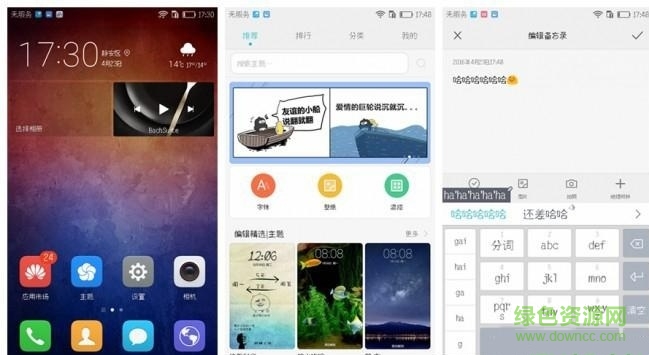
華為p9字體是一款非常漂亮的字體哦,這款字體是華為自帶的字體,當(dāng)時(shí)好像華為商城中是需要付費(fèi)才能下載哦,所以今天小編教大家怎么使用免費(fèi)的華為p9字體??!
注意:此字體偏小一些,在有些界面看上去會(huì)覺得小,可以將手機(jī)系統(tǒng)設(shè)置中的字體調(diào)大就可以了!另外,之前的華為手機(jī),出現(xiàn)過某些應(yīng)用的字體不能被替換,但P9測試完全可以!